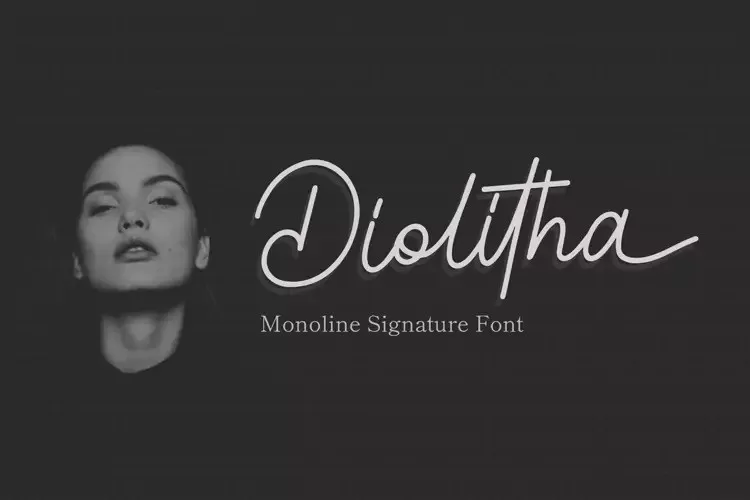
Diolitha Font – Fonte Grátis
Diolitha Font
A Diolitha Font é uma elegante tipografia script moderna, projetada para dar vida a designs que exalam sofisticação e naturalidade. Suas linhas leves e sutis criam um equilíbrio perfeito entre seriedade e charme, tornando-a uma escolha ideal para quem procura trazer um toque refinado a qualquer projeto. Sua versatilidade é impressionante: pode ser usada em rótulos de embalagens, logotipos, materiais de marketing ou até mesmo em letras menores, como títulos de slides de PowerPoint, mantendo sempre uma proporção perfeita e um estilo irresistivelmente atraente. Para quem busca uma fonte que combine elegância com simplicidade, a Diolitha Font é definitivamente para você.